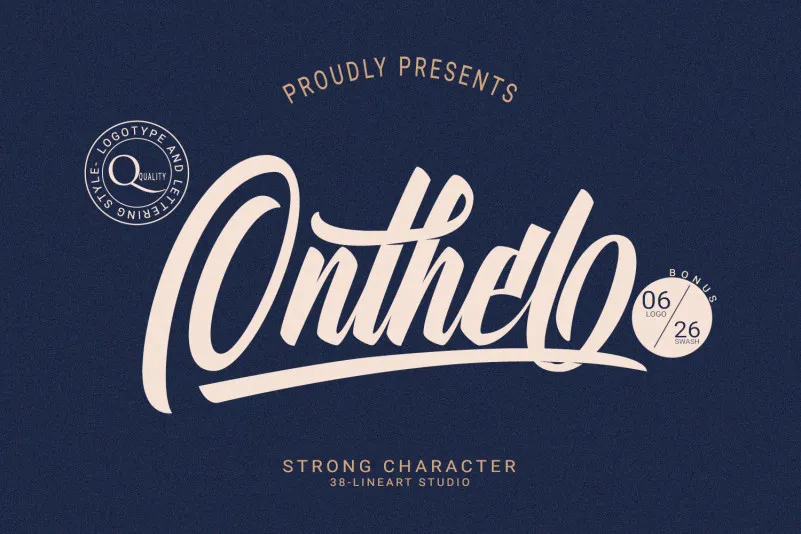
Onthel Calligraphy Font – Download Grátis
A fonte Onthel Calligraphy é uma escolha inteligente para logotipos e letraing. Inspirada na antiga e clássica marca de bicicletas Dónil, criada pela Onthel Bicycles que vem da Indonésia, esta fonte combina a robustez do design holandês com uma tração elegante, tornando-a perfeita para quem busca personalidade em seus projetos de logotipo ou letraing. Ela é uma escolha ótima para quem valoriza as linhas bold-script caracterizadas por um toque musical e a presença de um pincel, oferecendo um charme único e distintivo. Com Onthel Calligraphy, você pode adicionar ao seu trabalho um toque de sofisticação que se adapta perfeitamente aos designs modernos e contemporâneos.